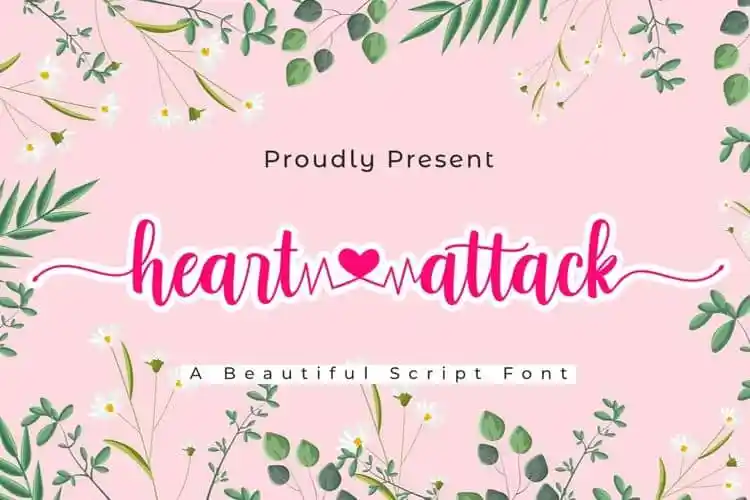
Heart Attack Calligraphy Font – Download Grátis
Introduzimos a Heart Attack Calligraphy Font, inspirada nas obras urbanas ou freestyle. Esta fonte oferece uma aparição casual ou marcadora com muitos alternantes estilizados que permitem criar cabeçalhos realistas. Foi criada pelo font designer Madatype Studio. Com seu ar carismático e elegante, a Heart Attack se destaca para diversas aplicações de design, incluindo convites de casamento, cartões de agradecimento, citações, cartas de cumprimentos, logotipos, cartões de negócios e todas as outras criações que precisam de um toque autêntico e manuscrito. É uma escolha inteligente para qualquer projeto que deseja dar um toque único e sofisticado à sua arte visual.